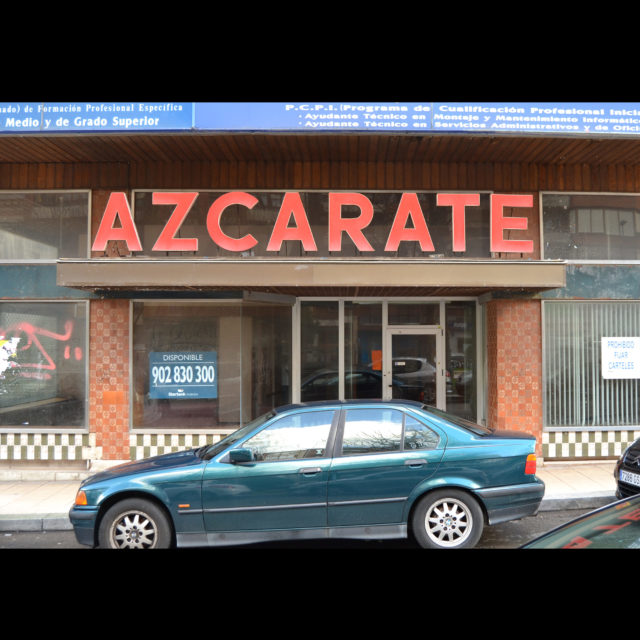
Identidad y Memoria
«Cuando hablamos de que los #rótulos son #patrimonio, no es a veces sólo porque se realizase de manera artesanal en vidrio, madera, cerámica o metal, si no también porque se hace parte intrínseca de un barrio o una calle. Se convierte en un icono visual de la memoria colectiva de la comunidad de la zona y del imaginario popular, que en muchos casos toma entidad propia y modifican el reconocimiento del territorio convirtiéndose en referente de la zona.»
Esto escribimos en 2020, a raíz de ver como un rótulo como el de «La Mejillonera» desaparecía. Recientemente vivimos un caso similar con el de «Azcárate» y al pasar por la zona, hemos podido comprobar el impacto e identidad visual que generaba esas letras, tras más de 50 años ahí puestas y su peculiar fachada con esa cerámica. Hoy el local se ha convertido en una franquicia, ha modificado su fachada y de algún modo impersonalizando el espacio.
De ahí que pidamos que se protejan esos elementos que también hacen ciudad y barrio. Y a esos comercios locales, a veces emblemáticos y sus historias, que se pueden esconder tras un simple trozo de plástico.
Por eso, mientras esto no se cumpla, es necesario poder preservarlos de su desaparición y que sigan formando parte de nuestro imaginario colectivo, así como parte de la historia más local. Y en ese trabajo estamos quienes amamos la tipografía, el diseño, la historia, la arquitectura, la cultura social, etc.
Seguiremos rescatándoles antes de pasen al olvido y nos lamentemos después viéndoles en fotos de archivo. Y ya estamos generando un gran archivo con los rescates que hemos ido haciendo, para de algún modo devolver a la sociedad estos objetos que forman parte de la Memoria Colectiva.
A veces son diseños simples, otros complejos, pero a fin y al cabo son Patrimonio Gráfico.